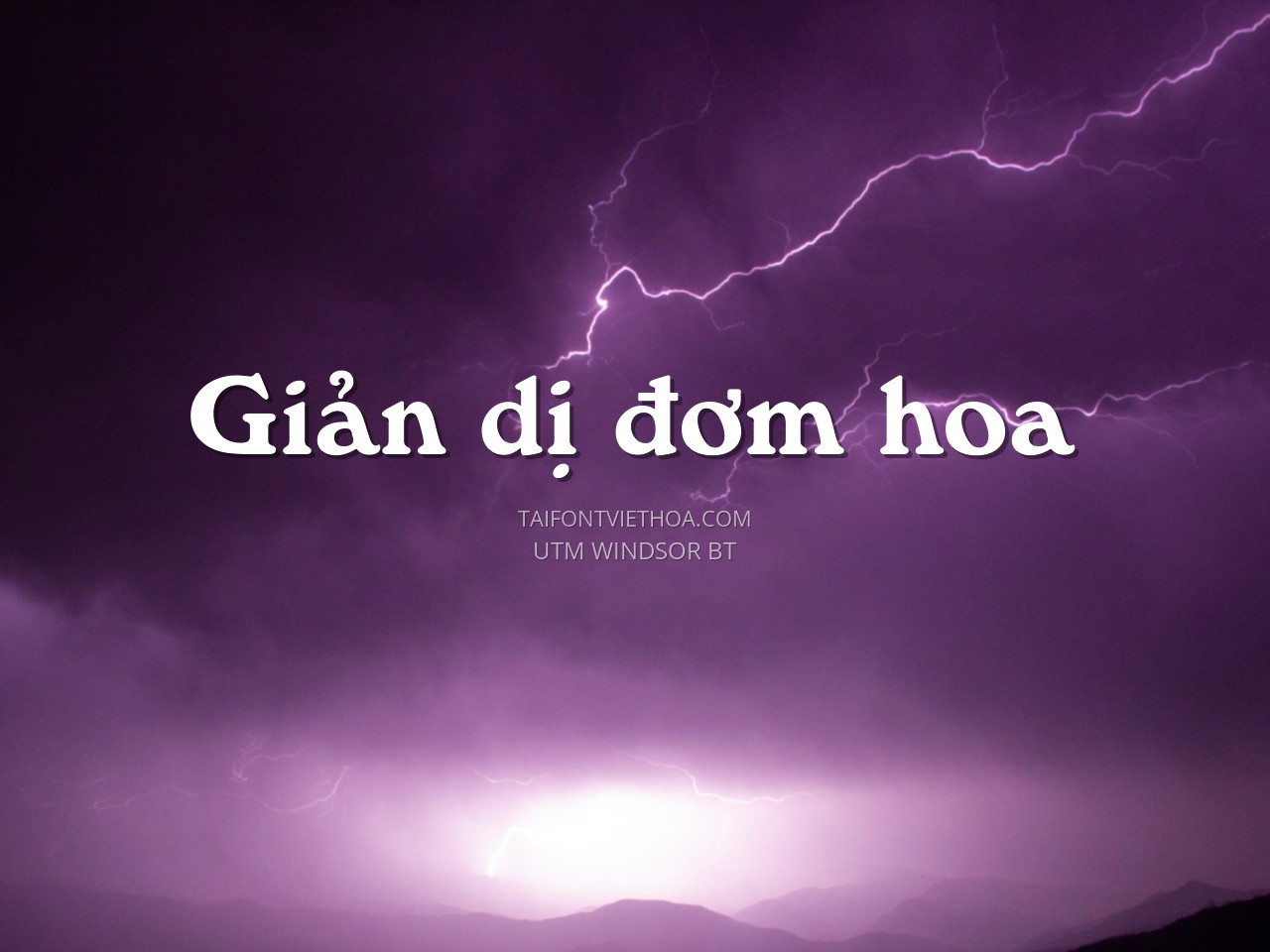
Font việt hóa UTM Windsor BT
Giới thiệu về font UTM Windsor BT – Kiểu chữ serif cổ điển và trang nhã
UTM Windsor BT là phiên bản Việt hóa của font Windsor BT – một kiểu chữ serif cổ điển nổi bật với thiết kế thanh lịch, mềm mại và cân đối. Font gốc được biết đến với các nét chân chữ mềm mại, tỉ lệ hài hòa và độ tương phản tinh tế, mang đến vẻ đẹp trang nhã và chuyên nghiệp cho các dự án thiết kế thương hiệu, ấn phẩm in ấn và truyền thông đa phương tiện. Phiên bản Việt hóa đã được hoàn thiện để hỗ trợ đầy đủ tiếng Việt cùng hơn 150 ngôn ngữ khác, mở rộng phạm vi sử dụng trong nhiều lĩnh vực sáng tạo.
Đặc điểm thiết kế và ứng dụng của UTM Windsor BT
UTM Windsor BT sở hữu cấu trúc serif với các nét chân chữ mềm mại, cân đối và thiết kế hài hòa. Font có nhiều biến thể trọng lượng, giúp các nhà thiết kế linh hoạt sử dụng trong nhiều bối cảnh từ tiêu đề nổi bật đến nội dung chi tiết. Thiết kế font mang lại cảm giác dễ đọc, trang nhã và chuyên nghiệp.
Font thích hợp sử dụng trong thiết kế sách, tạp chí, báo chí, thiệp cưới, bao bì sản phẩm và các dự án thương hiệu cao cấp. Các ngành nghề phù hợp gồm: xuất bản, giáo dục, nghệ thuật, tổ chức sự kiện và thiết kế nội thất.